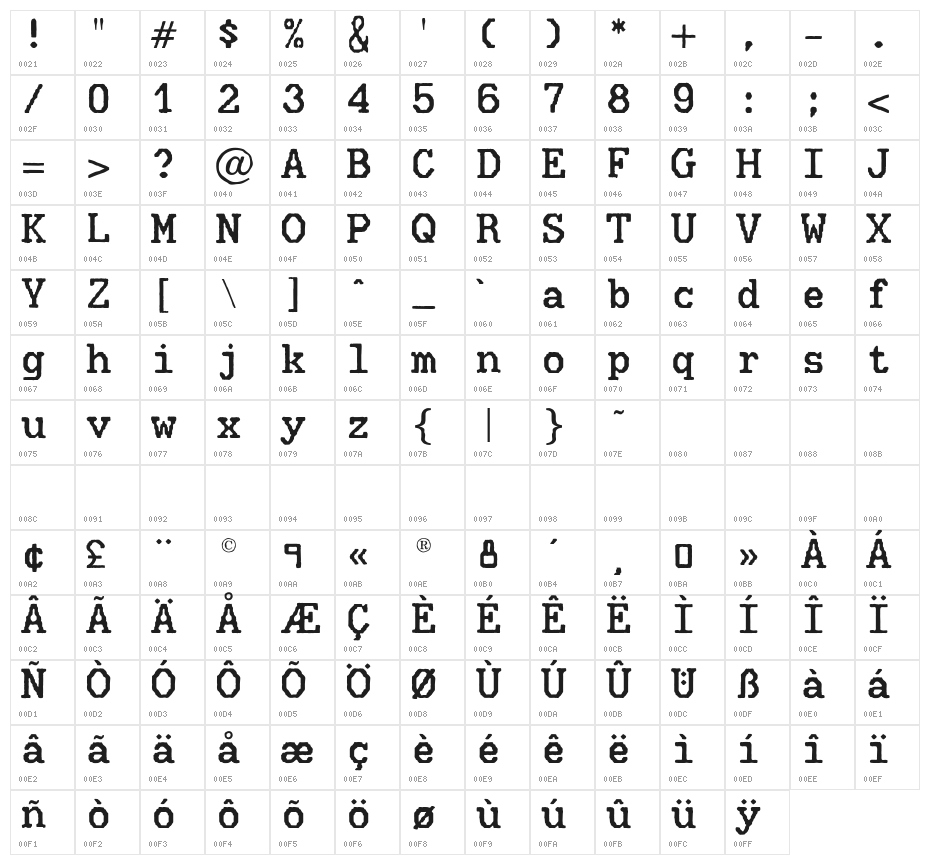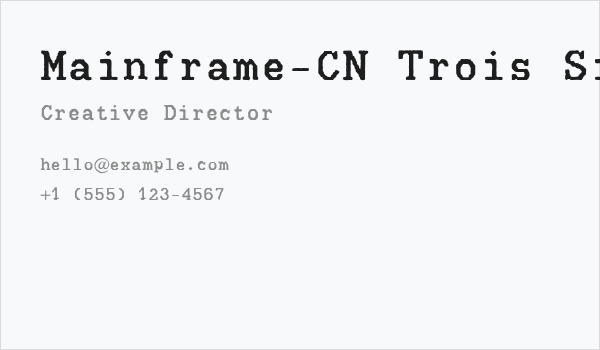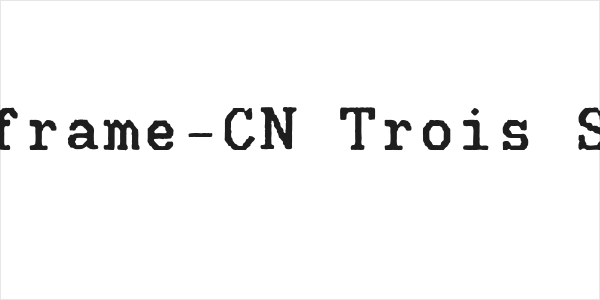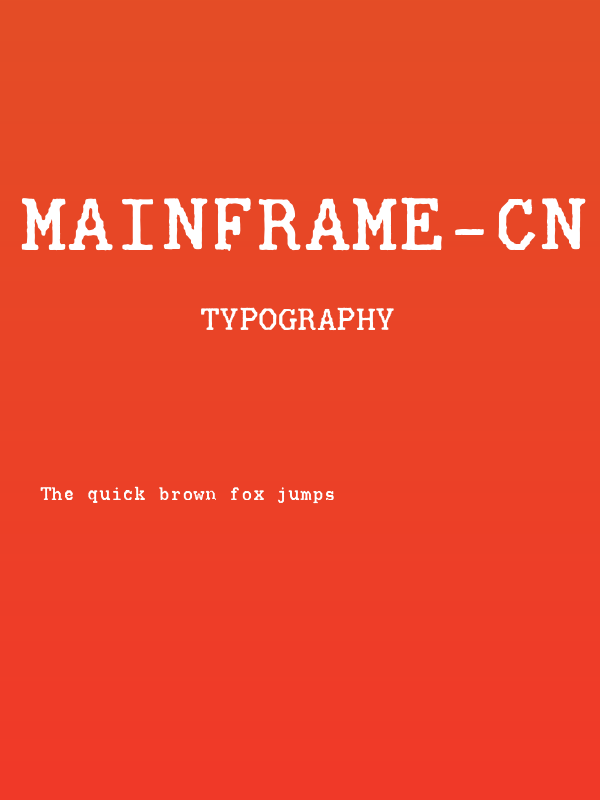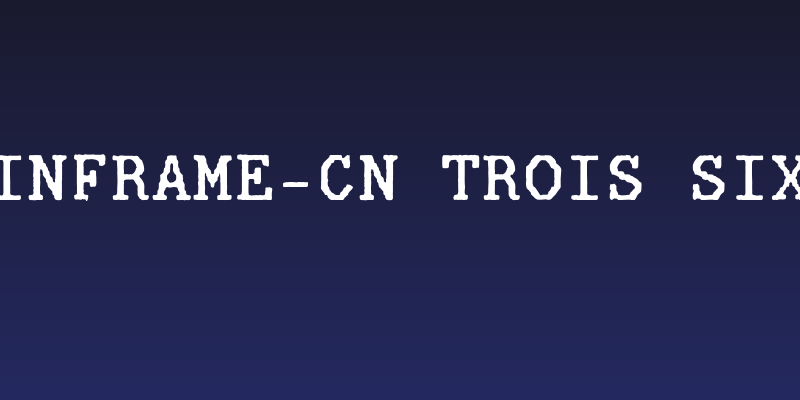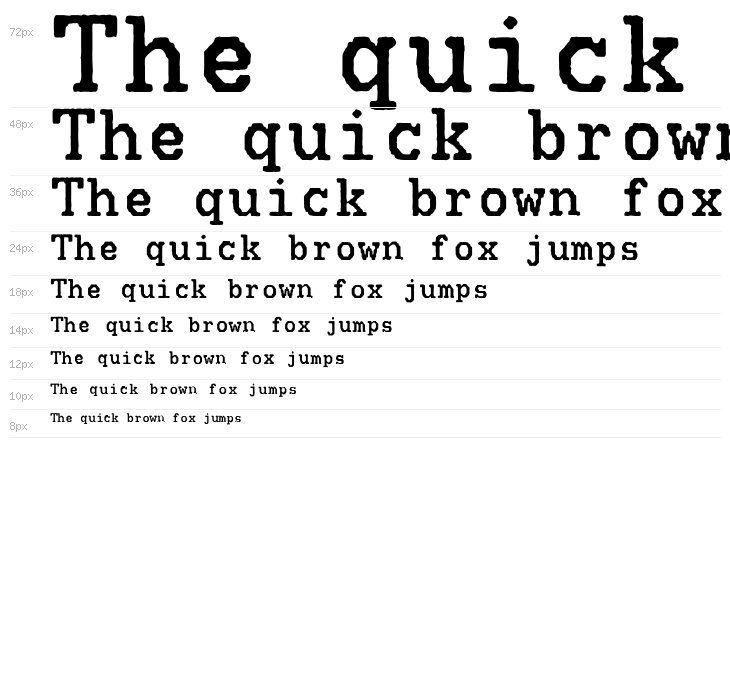
Mainframe-CN Trois Six R Font
| Gesamtstil | Vintage |
| Vorgeschlagene Projekte | Ideal for retro-themed designs, vintage posters, typewriter-style documents, and creative projects that require a nostalgic touch. |